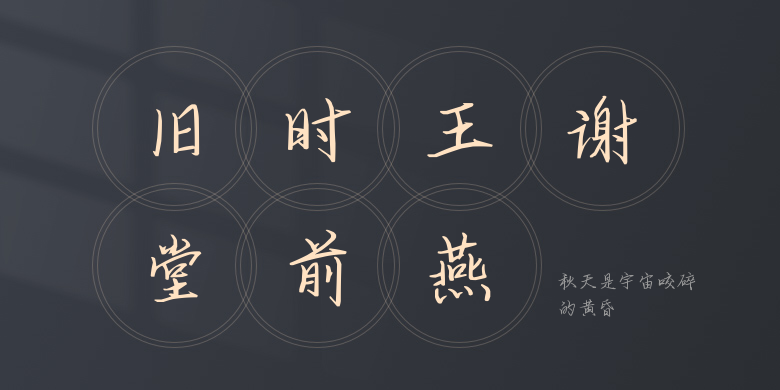
秋天是宇宙咬碎的黄昏
秋天是宇宙咬碎的黄昏,这款字体结构工整、笔画清晰,兼顾美观与易读性,适用于标题、正文、海报、包装、LOGO 等多种场景。字形优雅稳定,风格百搭耐看,适配日常排版与创意设计,让文字呈现更舒适、更具质感。秋天是宇宙咬碎的黄昏一笔一画,皆是细节,以均衡的比例、流畅的线条打造舒适视觉体验,字形端正大气,风格简约现代。无论是商业设计、品牌宣传还是日常排版,都能轻松驾驭,让文字更有格调与力量。秋天是宇宙咬碎的黄昏字体下载。